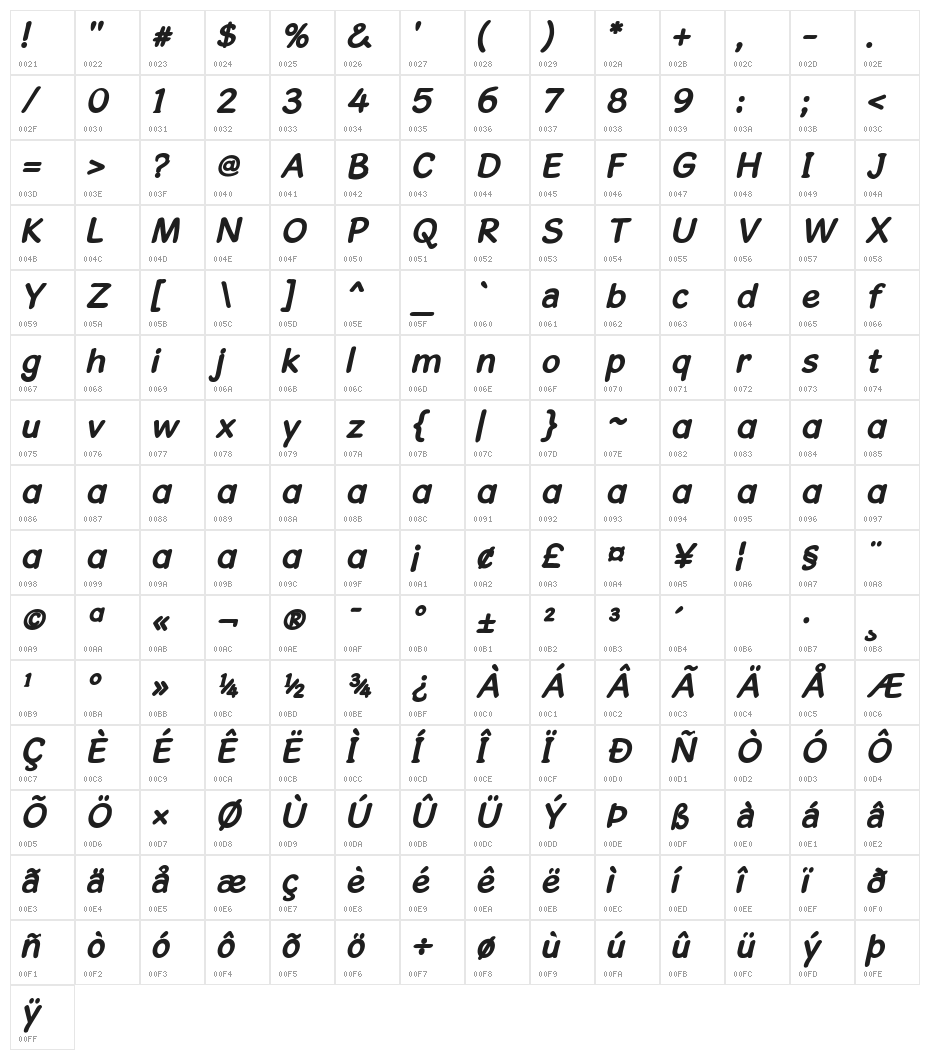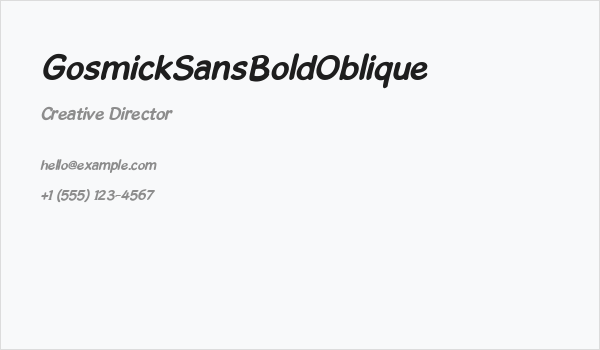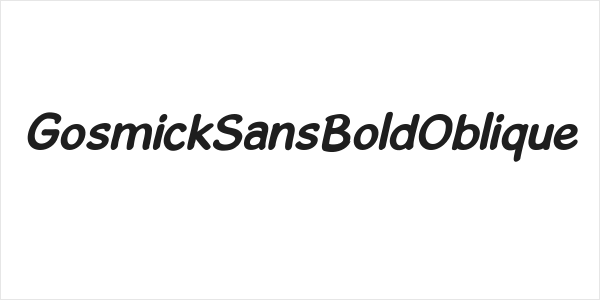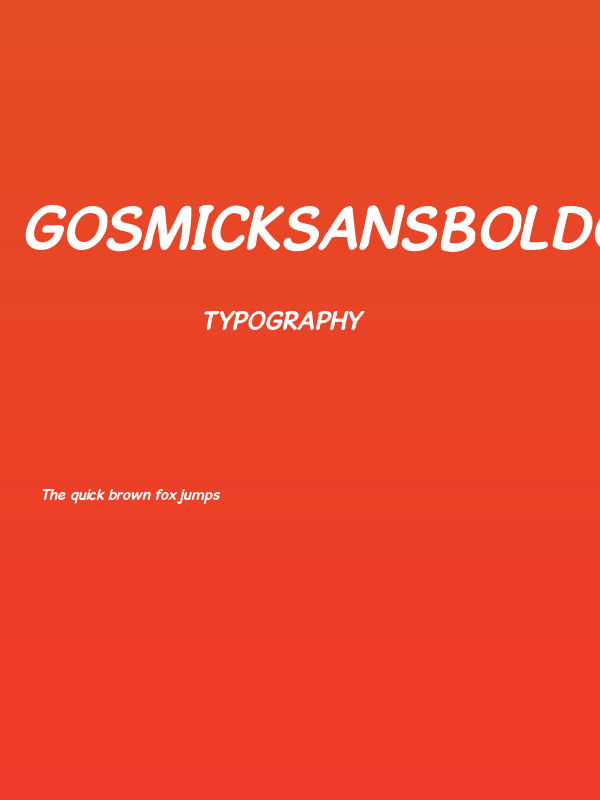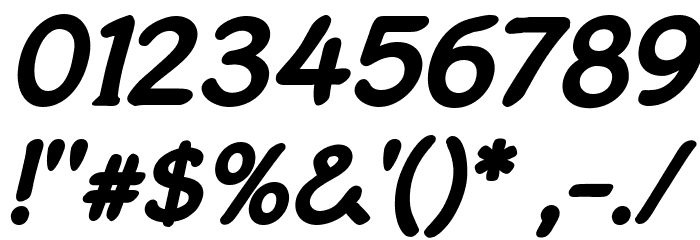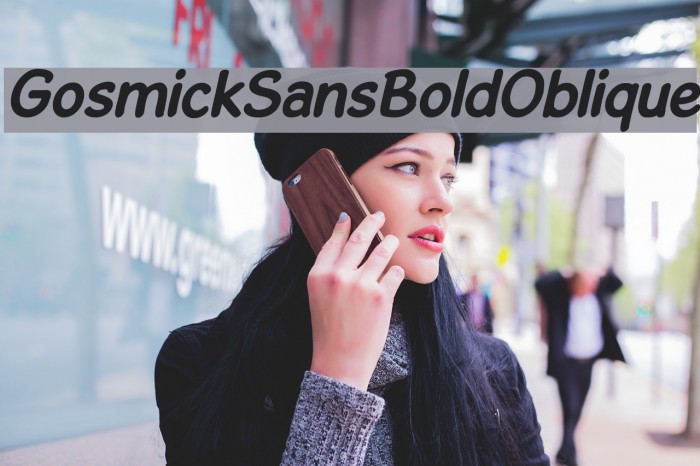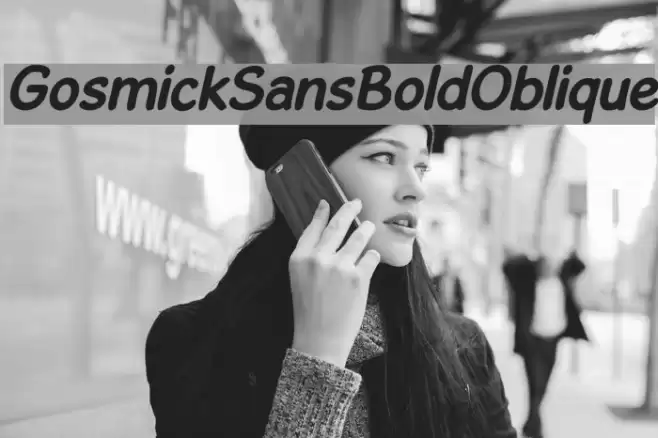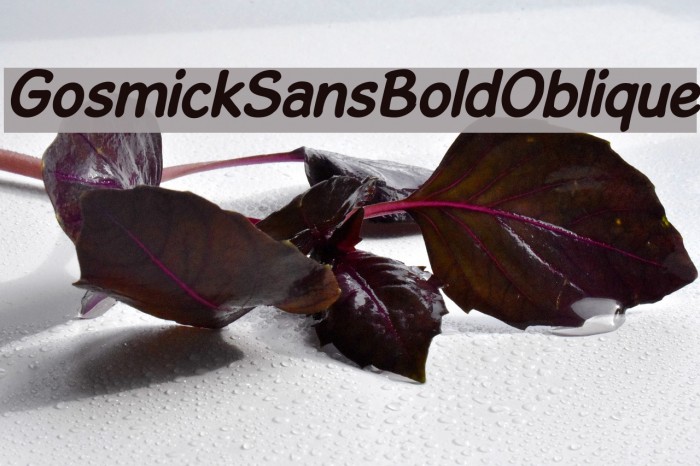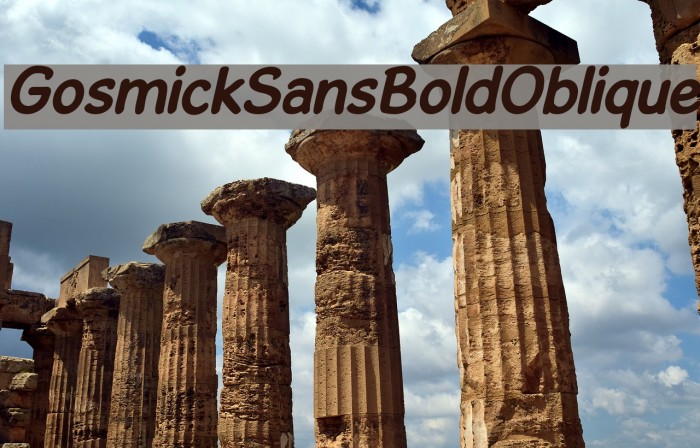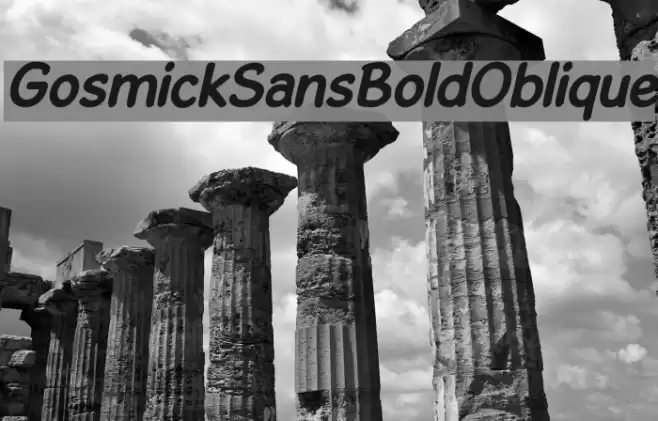
GosmickSansBoldOblique Font
| Poids | Bold Italic |
| Catégories | Comic |
| Cas d'utilisation | Headlines, Logos, Advertising |
| Projets proposés | Ideal for branding, advertising, headlines, and playful design projects that require a bold statement. |